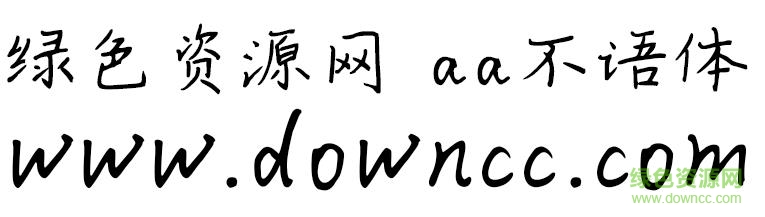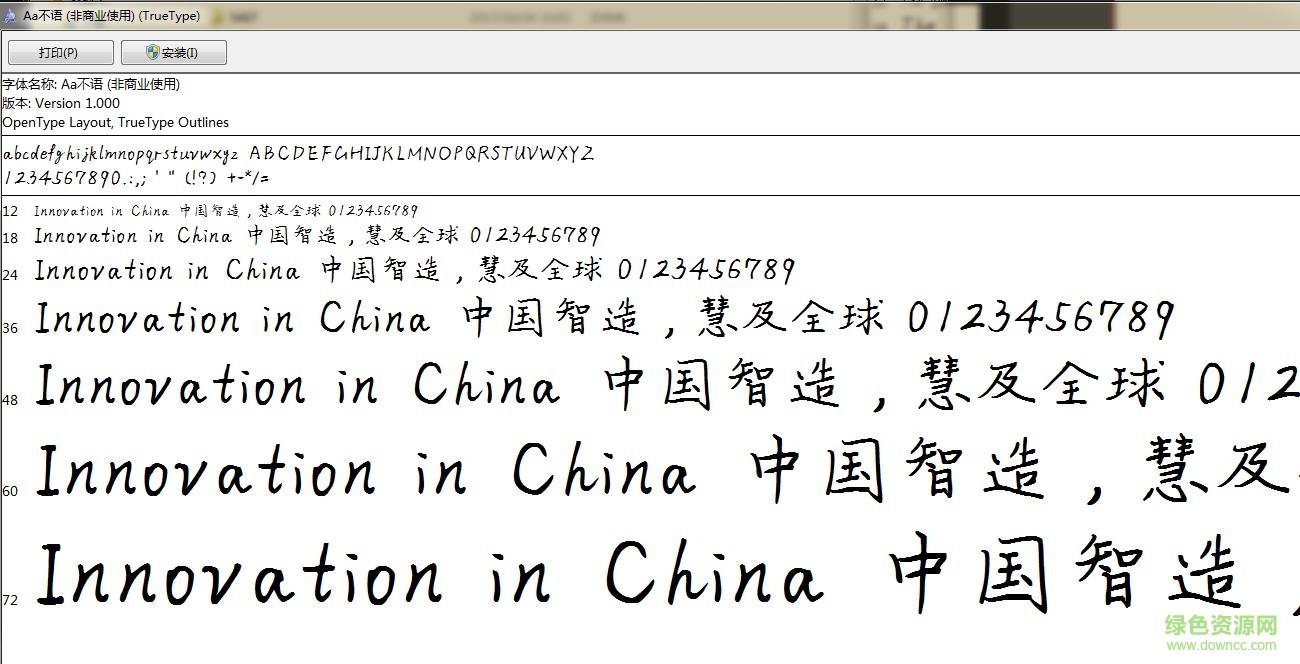
aa不語體字體很好看哦,這款字體樣式很隨意,每一個字都十分的放松,讓你看著很舒服,而且結(jié)構(gòu)很規(guī)整,在很多行業(yè)中使用都能夠得到不錯的效果,快來綠色資源網(wǎng)下載吧!
1、字體在不斷的演變中逐步的適應(yīng)了各類用戶所需的效果,展現(xiàn)出了字體的獨(dú)特魅力
2、字體能夠經(jīng)過各類變換,從而生成一種全新的字體風(fēng)格,用以相應(yīng)的字體顯示